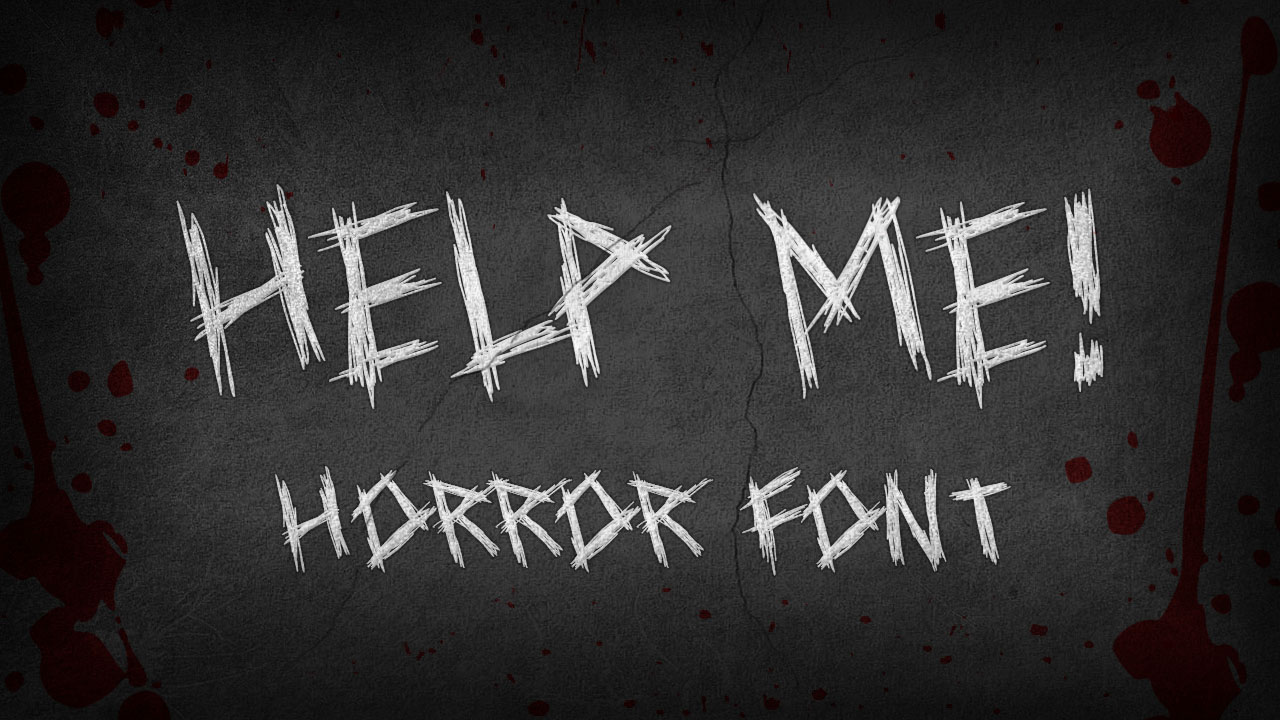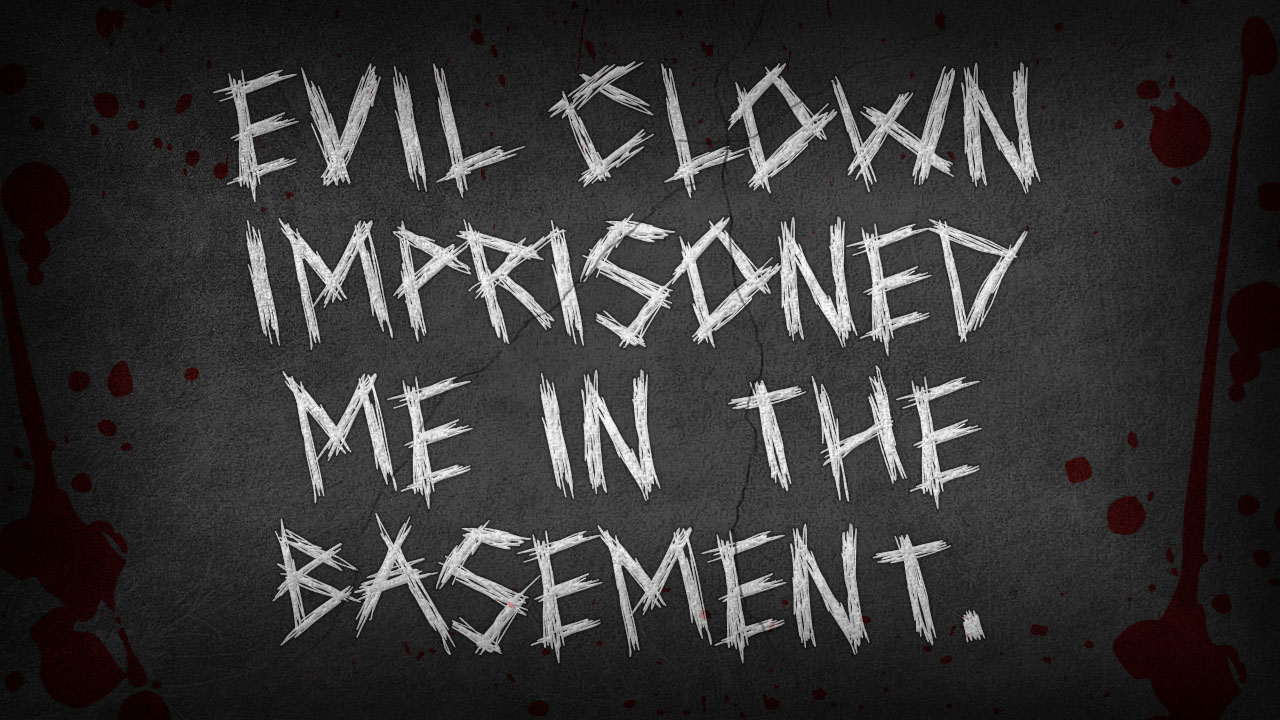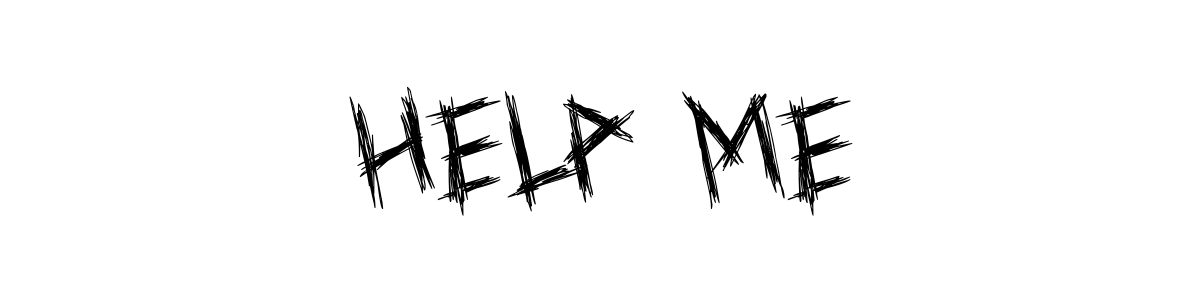
Help Me
Help Me 是一款模拟在粗糙表面(如混凝土或木质)上划伤痕迹的免费英文字体,以其原始、粗粝的手工质感为特征。其设计核心在于完全模仿手工划刻的视觉效果,包含了英文大小写字母、数字及基本标点符号在内的 104 个字形。
字体的每个字符都如同使用尖锐物在坚硬表面上费力凿刻而成,笔画充满了不规则的断裂、毛刺和深浅不一的变化。作为一款风格极端且单一的字体,其全部表现力都凝聚在这种独特的“划伤”质感之中,适用于需要强烈情绪或特定纹理感的视觉创作。
Help Me 摒弃了传统字体的平滑轮廓与几何精度,追求一种即时、粗暴且充满情绪化的物理介入感。字体笔画呈现出一种不连贯的“虚线”或“刮擦”效果,边缘破碎,仿佛在抵抗材料本身的过程中形成了最终的形态。这种设计创造出强烈的张力与不稳定感,散发着原始、焦虑、反叛或挣扎的气息。